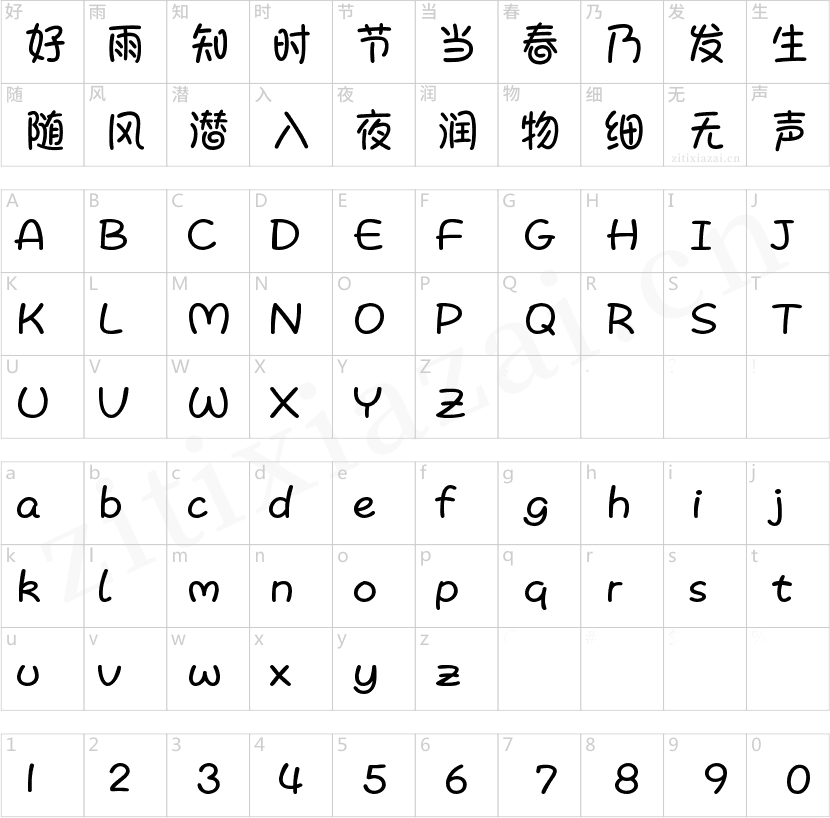
Aa咘咘减细
Aa咘咘减细,这款字体结构工整、笔画清晰,兼顾美观与易读性,适用于标题、正文、海报、包装、LOGO 等多种场景。字形优雅稳定,风格百搭耐看,适配日常排版与创意设计,让文字呈现更舒适、更具质感。Aa咘咘减细一笔一画,皆是细节,以均衡的比例、流畅的线条打造舒适视觉体验,字形端正大气,风格简约现代。无论是商业设计、品牌宣传还是日常排版,都能轻松驾驭,让文字更有格调与力量。Aa咘咘减细字体下载。
Aa咘咘减细字体
Aa咘咘减细是一款非常具有艺术性的字体,它的设计灵感来源于对古典艺术的研究,同时又融入了现代字体设计的元素。字形优美,笔画粗细变化自然,给人以大气、典雅的感觉。Aa咘咘减细是一款既传统又现代的字体,它的设计充满艺术感,美观大方,实用性也非常强。无论是对于设计师还是对于普通读者来说,都是一种非常不错的字体选择。Aa咘咘减细适合用于具有艺术感的场合,比如海报、宣传单张、书籍封面等。由于其字形流畅且具有动态感,也适合用于大量的文本排版,如报纸、杂志等。